サンセリフ体は一見シンプルですが、種類や印象の違いを正しく理解することが、書体選びの精度を大きく高めます。この記事では、デザイン初心者にもわかりやすく、サンセリフ体の基本や分類、代表的な書体を丁寧に整理しました。
「何を選べばいいかわからない」と感じていた方こそ、ぜひ一度、基礎から確認してみてください。
サンセリフ体とは?
サンセリフ体(Sans-serif typeface)とは、文字の端にある「セリフ(serif)」と呼ばれる小さな飾りが付いていない書体のことです。
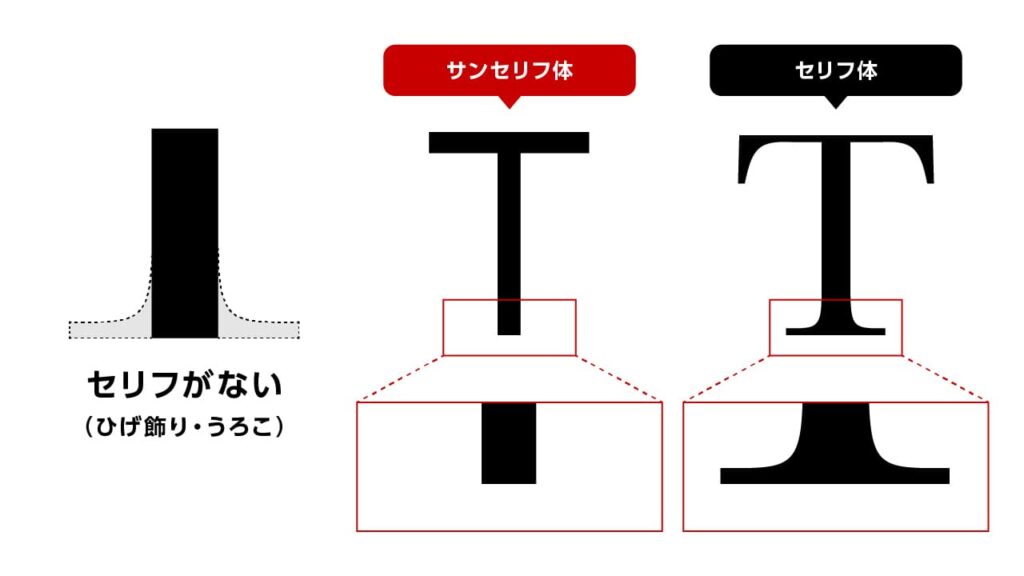
「sans」はフランス語で「〜が無い」という意味で、その名の通りセリフを省いたシンプルなデザインが特徴です。セリフ体(ローマン体)が文字の端に装飾を持ちクラシックで伝統的な印象を与えるのに対し、サンセリフ体は装飾のない分よりクリーンでモダンな印象を与え、デジタル画面でも読みやすいとされています。なお、欧文のサンセリフ体は日本語書体で言うところの「ゴシック体」に相当し、明朝体(セリフのある書体)と並ぶ基本的なカテゴリーです。サンセリフ体は簡潔な字形ゆえに視認性が高く悪条件下でも文字が判別しやすいという利点があり、新聞見出しや道路標識などパッと一瞥で内容を伝える場面で重宝されます。ただし従来、長文の可読性においてはセリフ体に劣るとも言われ、小説など連続した文章よりも見出しや短文向きの書体と位置付けられてきました。
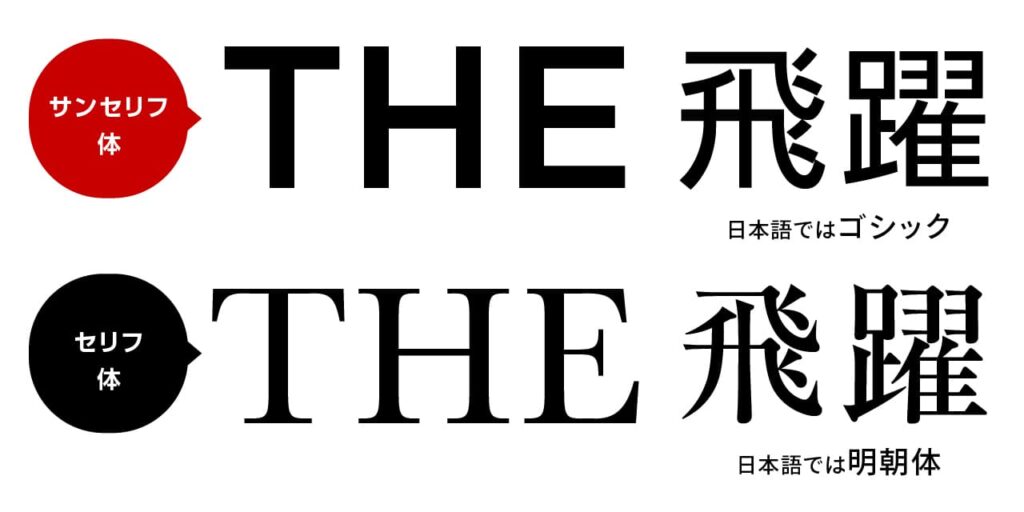
本記事では、サンセリフ体の歴史や分類、用途と印象の違い、さらに定番フォントの紹介と選び方のポイントについて解説します。セリフ体の基礎に続く内容として、デザイン初心者の方にも分かりやすくサンセリフ体の奥深い世界を見ていきましょう。
サンセリフ体の歴史的背景
サンセリフ体が登場したのは19世紀に入ってからで、書体の中では比較的新しい歴史を持つカテゴリーです。19世紀前半、工業化とともにポスターやチラシなど商業印刷物が発達する中で、遠くからでも目を引きはっきり読めるシンプルな見出し用書体が求められ、最初期のサンセリフ体の活字が生み出されました。当初この新奇な書体は「グロテスク(Grotesque)」あるいは「ゴシック(Gothic)」と呼ばれ、当時代表的なものにAkzidenz Grotesk(1898年、ドイツ)やFranklin Gothic(1902年、アメリカ)などがあります。これら初期のサンセリフ体は装飾を削ぎ落とした力強いデザインで、広告の見出しや看板などに活用されました。
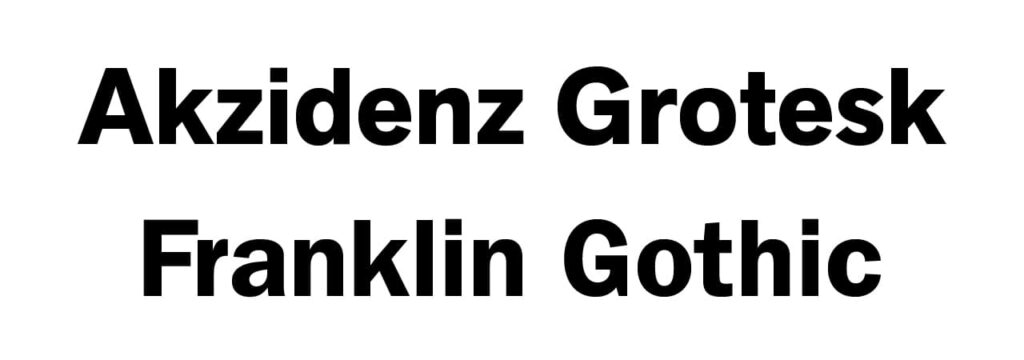
20世紀に入るとサンセリフ体はグラフィックデザインの潮流に合致したモダンで洗練されたルックスにより広く人気を博すようになります。例えば1920〜30年代には幾何学的デザインのFuturaや、古典書体のエッセンスを取り入れたGill Sansなどが登場し、さらに1950年代にはスイスを中心とする国際タイポグラフィ様式のもとでHelvetica(ヘルベチカ)やUnivers(ユニバース)といった洗練されたサンセリフ体が次々と開発されました。こうした書体は印刷物だけでなく企業のロゴやサイン計画にも採用され、サンセリフ体の地位を不動のものとしました。
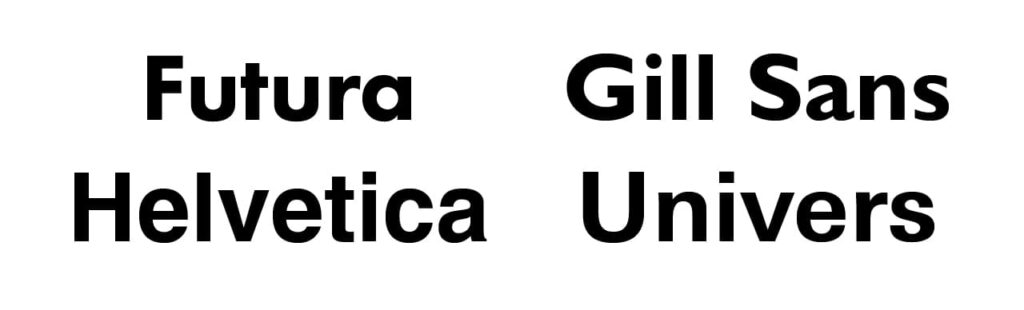
なお、サンセリフ体は以前「ゴシック体」と呼ばれることもありましたが、欧米では“Gothic”はブラックレター(黒字書体)を指すため紛らわしく、現在は国際的に「Sans-serif(サンセリフ)」という呼称に統一されています。
デジタル時代に入ると、サンセリフ体はその直線的でそぎ落としたデザインゆえに画面上で特に読みやすく、ウェブやユーザインタフェースの基本フォントとして欠かせない存在となりました。こうして約200年ほどの歴史の中で、サンセリフ体は印刷物からデジタル媒体まで幅広く活躍するモダン書体として定着しています。
サンセリフ体の主な分類と特徴
ひと口にサンセリフ体と言っても、そのデザイン上の特徴から大きく4つのグループに分類することができます。以下にグロテスク(Grotesque)、リアリスト(Realist)、 ヒューマニスト(Humanist)、ジオメトリック(Geometric)というサンセリフ体の主な分類とそれぞれの特色を説明します。
グロテスク・サンセリフ
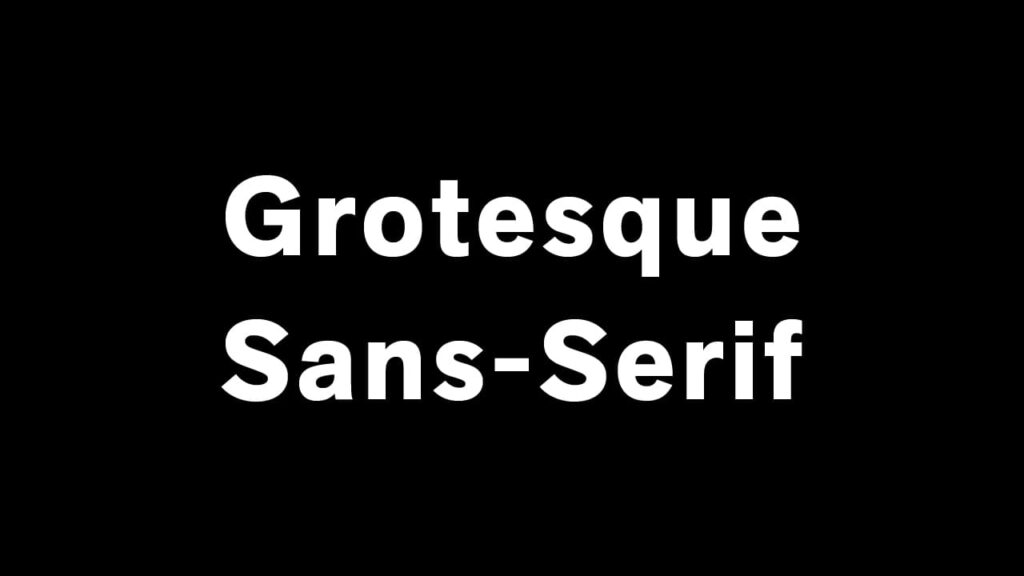
書体の特徴と背景
グロテスク・サンセリフは、サンセリフ体の最初期に登場した書体群で、19世紀から20世紀初頭にかけて生まれました。直線的で力強く、装飾のないシンプルなデザインが特徴で、当時はその異質な見た目から「グロテスク(奇妙)」と呼ばれました。
字幅の太さや端の処理にやや粗さがあり、全体的に武骨で頑丈な印象を与えます。視認性が高く、インパクトのあるデザインが求められる場面に適しています。
代表的な書体
- Akzidenz Grotesk(アクチデンツ・グロテスク)
ドイツで生まれ、後の多くのサンセリフ体に影響を与えた先駆的書体。 - Franklin Gothic(フランクリン・ゴシック)
アメリカで開発され、広告や新聞の見出しなどに多用された、力強さのあるフォント。
使用シーン
太く力強いグロテスク体は、ヴィンテージ感や男性的な印象を与えたいデザイン、広告・ポスター・見出しなどに最適です。
リアリスト・サンセリフ(ネオ・グロテスク)
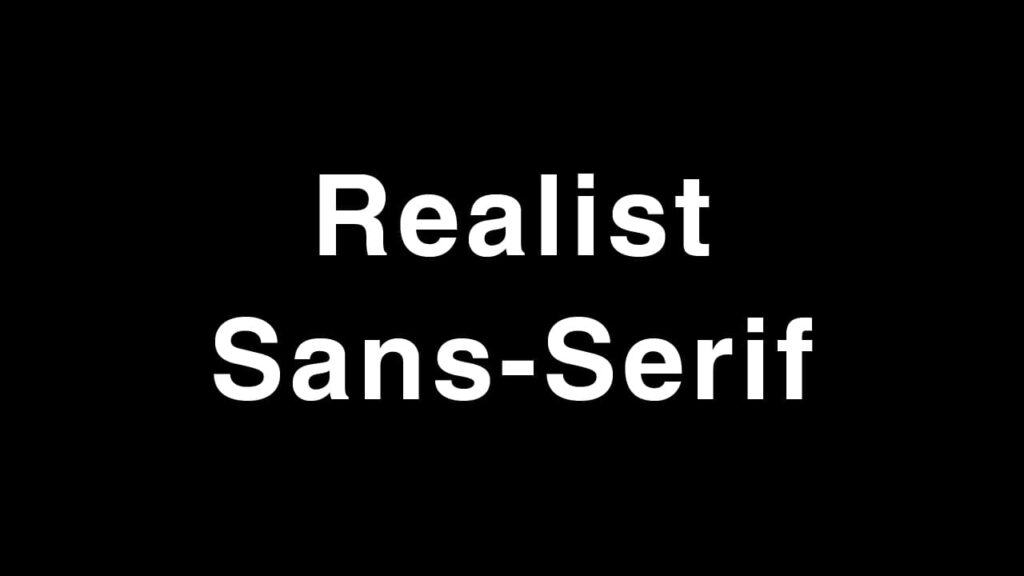
書体の特徴と背景
リアリスト・サンセリフは、グロテスク体を洗練し、より現代的に整えたスタイルです。1950年代前後に登場し、「ネオ・グロテスク」とも呼ばれます。
癖の少ないスマートな字形、均一な線幅、高い視認性と汎用性が特徴で、どんな媒体にも適応する中立的かつ万能なフォントです。
代表的な書体
- Helvetica(ヘルベチカ)
スイス生まれ。世界的に使用されており、ロゴ・標識・UIなど幅広い用途に対応。 - Univers(ユニバース)
多様なウエイト・スタイルを持つ、体系的に設計されたフォントファミリー。 - Arial(エリアル)
Microsoftに標準搭載された汎用フォント。画面表示に強く、文書やウェブにも適しています。
使用シーン
資料・UI・ウェブ・コーポレートデザインなど、癖のない安定感を求める場面に広く活用されます。
ヒューマニスト・サンセリフ
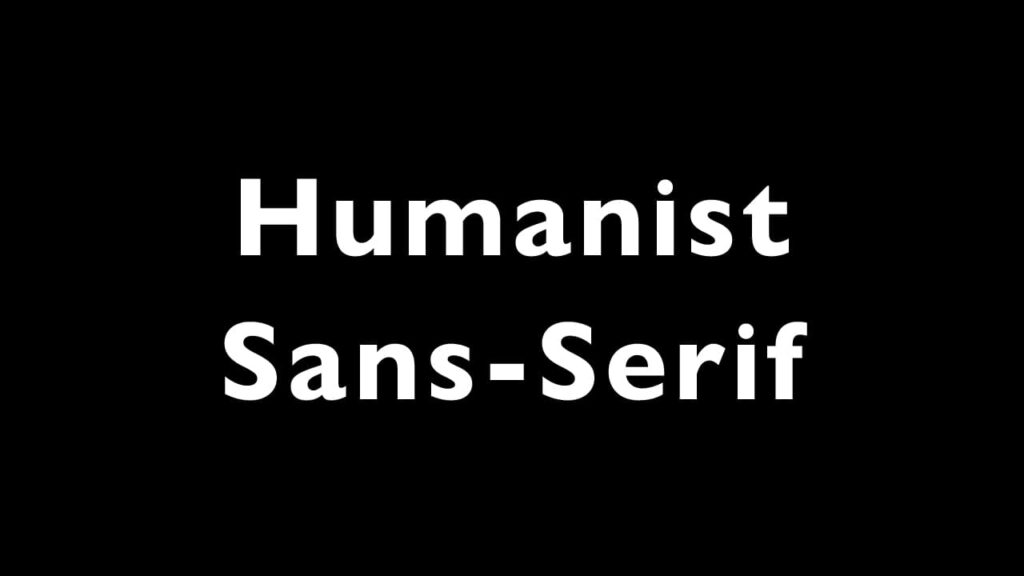
書体の特徴と背景
ヒューマニスト・サンセリフは、人の筆記のニュアンスを反映した、人間味のあるデザインが特徴です。古典的なセリフ体の骨格をベースにし、滑らかな曲線と抑揚のあるストロークが温かみを生み出します。
「読みやすさ」だけでなく、「優しさ」や「親しみやすさ」といった感情的な印象を与えるサンセリフ体です。
代表的な書体
- Gill Sans(ギル・サン)
英国で開発され、公共デザインやテレビ局などに多く採用。柔らかく上品な印象。 - Frutiger(フルティガー)
空港サイン向けに開発。可読性が非常に高く、案内表示などに多用。 - Verdana(ヴァーダナ)
画面表示用に最適化されたデザイン。小サイズでも読みやすく、WebやUIに強い。
使用シーン
教育・医療・公共サインなど、人にやさしく寄り添う印象を与えたいときに適しています。
ジオメトリック・サンセリフ
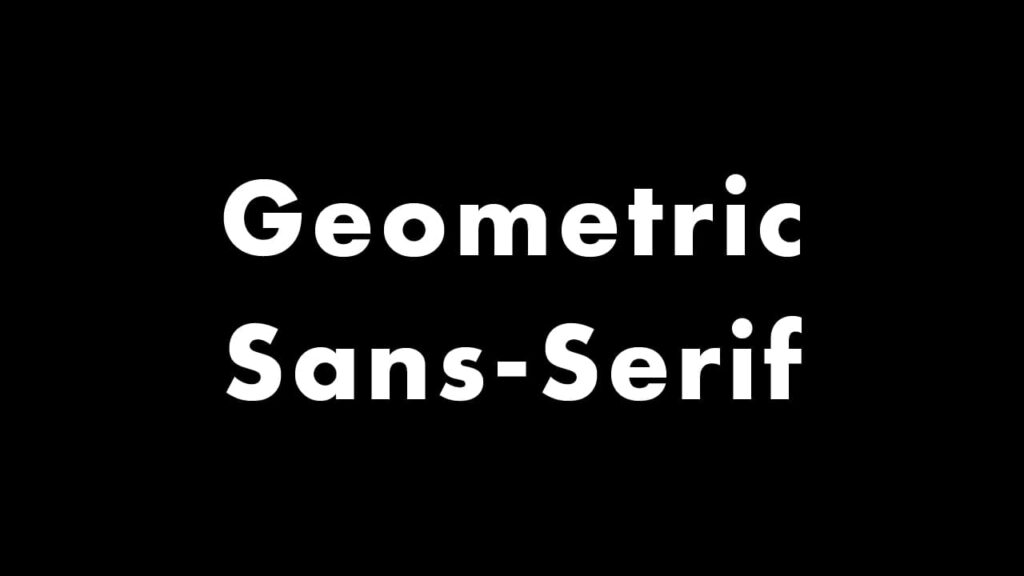
書体の特徴と背景
ジオメトリック・サンセリフは、円・直線・三角形などの幾何学図形を基に設計された書体です。1920年代のドイツ・バウハウスの思想を背景に誕生し、構造的でモダンなデザインが特徴です。
均整の取れた美しい字形は、先進性・創造性・理知的な印象を与えます。
代表的な書体
- Futura(フーツラ)
幾何学デザインの先駆け。シンプルかつ未来的な印象で、ロゴやポスターに人気。 - Avenir(アベニール)
Futuraに比べて読みやすさを重視。バランス感があり、本文にも対応。 - Gotham(ゴッサム)/ITC Avant Garde
ロゴやブランド用として人気。洗練されたスタイルで現代的な印象を演出。
使用シーン
ファッション・IT・広告など、ブランドの先進性やスタイリッシュさを訴求したいデザインに最適です。
サンセリフ体の用途と印象
サンセリフ体は、視認性・中立性・現代性を備えた非常に実用性の高い書体であり、紙媒体からデジタル、公共から広告、教育からビジネスまで幅広い用途に対応できる汎用性があります。
伝えたい印象や用途に応じて適切なサンセリフ体を選ぶことで、デザインの説得力や完成度を大きく高めることができます。
サンセリフ体が持つ基本的な印象とは
サンセリフ体は、装飾のないクリーンな字形と高い視認性から、さまざまな場面で重宝される書体です。セリフの有無による印象の違いは、デザインメッセージの伝わり方に直結します。
たとえば、セリフ体は「伝統的」「格式が高い」「権威的」といった印象を持たせやすく、証書や招待状などフォーマルなデザインに向いています。一方、サンセリフ体は「新しさ」「モダンさ」「カジュアルさ」を表現しやすく、ハイテク企業のウェブサイトや先進的な印象を打ち出したい場面に適しています。
実用性の高さと視認性の強さ
サンセリフ体のもうひとつの大きな強みは、小さなサイズでも潰れにくく、遠目でも認識しやすいという点です。これは、ストロークに装飾的な突起がないためです。
そのため、道路標識、取扱説明書、新聞や辞書の見出し、広告ポスターなど、一目で情報を伝えたい媒体で広く使用されています。また、プレゼン資料やインフォグラフィックスでも、サンセリフ体は読みやすく、プロフェッショナルな印象を与えるため、ビジネスシーンにも適しています。
デジタルメディアとの相性の良さ
サンセリフ体は、デジタル環境でも非常に高い可読性を発揮します。
ディスプレイの解像度が低い場合でも、セリフのような細かな装飾がないため、文字の視認性が損なわれにくいという利点があります。そのため、ウェブサイトやモバイルアプリ、ソフトウェアUIでは、サンセリフ体が基本書体として選ばれることが多く、実際に、WindowsのSegoe UIやMacのSan Franciscoなど、主要OSの標準フォントもすべてサンセリフ体で構成されています。
印象を変えるフォントの個性
「サンセリフ体=無個性」ではありません。むしろ、装飾が少ない分、フォントの骨格そのものの表情が際立ちます。そのため、選ぶフォントによって与える印象は大きく変わります。
- ヒューマニスト系:柔らかく親しみやすい印象。教育・公共の場に最適。
- リアリスト系:ニュートラルで信頼感のある印象。金融・法律・ビジネス用途に適す。
- ジオメトリック系:スタイリッシュで先進的な印象。ハイテク・ファッションブランドに人気。
実際、GoogleやFacebookをはじめ、多くのグローバル企業がサンセリフ体のロゴを採用しているのは、ニュートラルでフラットな印象が、多様な文化背景を持つユーザーにも受け入れられやすいためです。
定番のサンセリフ体フォント紹介
ここではデザイナー志望なら知っておきたい定番のサンセリフ体フォントを、前述の分類ごとにいくつか紹介します。それぞれのフォントの特徴や使用シーンの例も添えますので、ぜひ実際に使ってみる際の参考にしてください。また、紹介するフォントはAdobe Fontsで使用できますので、リンク情報を貼っておきますね。
グロテスク・サンセリフの定番フォント
Akzidenz Grotesk
Akzidenz Grotesk(アクチデンツ・グロテスク)は1898年にドイツで生まれた最初期のサンセリフ体の一つ。無駄のないシンプルなデザインで後のHelveticaなど多くの書体のお手本となりました。太さや大きさを変えた幅広いファミリー展開があり、中立的で癖のないスタイルは企業デザインから標識まで幅広い用途で利用されています。
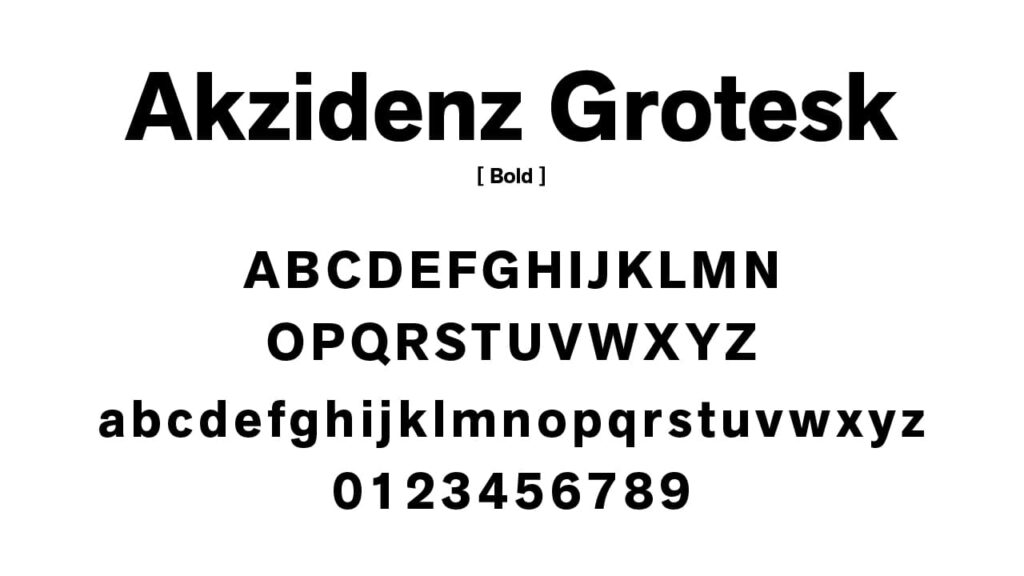
Franklin Gothic
Franklin Gothic(フランクリン・ゴシック)は、1902年にアメリカで発表されたグロテスク体書体。古典的でやや粗削りな力強さが持ち味で、男性的で堂々とした雰囲気を醸し出します。見出しやポスターでインパクトを与えたい時に適しており、新聞の見出しや大学スポーツチームのロゴなどにも用いられました。太く大ぶりな字形は遠目にも目立つため、広告物で強い存在感を放ちます。
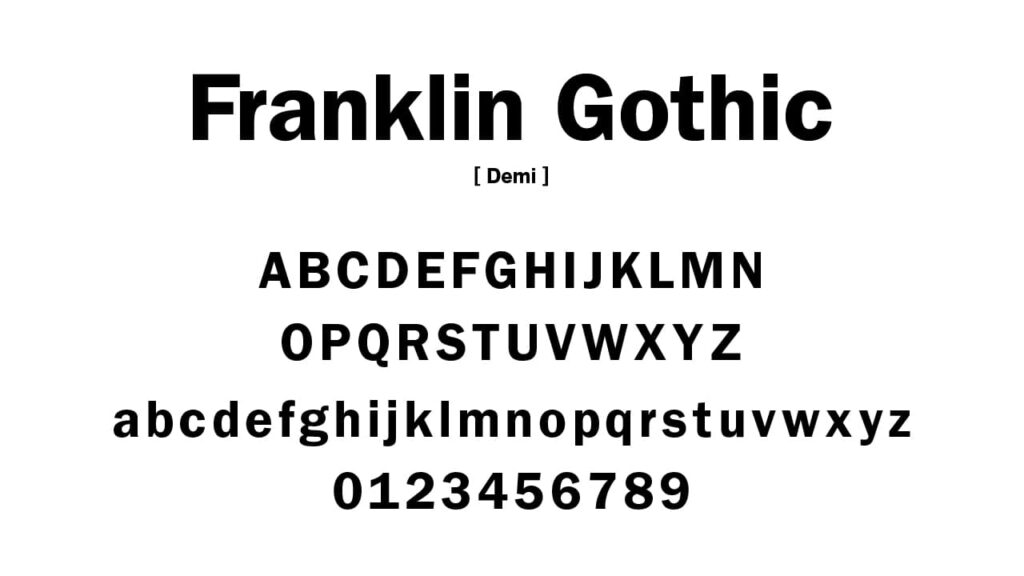
DIN
DIN(ディン)は20世紀前半にドイツ工業規格(DIN)として制定されたサンセリフ体で、道路標識や案内表示に採用されたことでも有名です。直線的で均一なストロークによる工業的デザインは可読性が高く、無駄のないクールな印象を与えます。現代ではその洗練されたスタイルから、モダンでミニマルなブランドのロゴや、サイエンス・テクノロジー系のデザインなどにも広く活用されています。
リアリスト・サンセリフの定番フォント
Helvetica
Helvetica(ヘルベチカ)は1957年にスイスで生まれ、世界で最も愛用されているサンセリフ体の一つです。名前はラテン語で「スイス」を意味する「Helvetia」に由来します。シンプルで洗練された美しさを持ち、ニュートラルかつ汎用的なデザインであることから多数の企業ロゴや公共サインに採用されています。例えばニューヨーク市地下鉄の標識やユニクロのロゴなど、 Helvetica が使われた有名な例は数えきれません。どんな媒体でも安定して読みやすく、「究極のスタンダードフォント」として知られます。
Univers
Univers(ユニバース)は、Helveticaと同じ1957年に生まれたフランス発のサンセリフ体。デザイナーのエイドリアン・フルティガーによって体系的なファミリーとして設計されたことが特徴で、太さや幅の異なる21種類ものバリエーションを持つ包括的なフォントファミリーです。字形のデザインは非常に均整が取れており、Helveticaよりやや人間味のある柔らかさも備えています。印刷物からディスプレイまで万能に使える書体として、スイス航空やモトローラ社のコーポレートフォントに採用されるなど信頼性の高いブランド表現に貢献してきました。
Arial
Arial(エリアル)は1982年に開発され、現在ではWindowsやOffice製品に標準搭載されているため誰もが目にしたことのあるサンセリフ体です。Helveticaに似たデザインを持ちつつ画面表示に最適化されており、デジタル文書やWeb上の標準フォントとして広く利用されています。特にウェブの本文やプレゼン資料のテキストなど、読み手の環境を問わず確実に表示させたい場面で重宝されます。Arial自体はデザイン的に強い個性を主張しない分、内容を邪魔せず情報伝達に徹する実用的なフォントと言えます。
ヒューマニスト・サンセリフの定番フォント
Gill Sans
Gill Sans(ギル・サン)は1928年にイギリスのエリック・ギルによってデザインされた書体で、ヒューマニスト・サンセリフを代表するフォントの一つです。古典的なトラジャン石碑の文字にヒントを得たプロポーションを持ち、優雅さとモダンさを兼ね備えた独特の風格があります。イギリスでは国営鉄道のサインやBBCのロゴなどに採用され、公共的で信頼感のあるイメージを与えてきました。柔らかな曲線とオープンな字面により、堅苦しすぎず親しみやすい印象を与えるため、教育・文化施設や雑誌のデザインなどにも適しています。
Frutiger
Frutiger(フルティガー)は、1975年にスイス人デザイナーのエイドリアン・フルティガーによって制作されたフォントで、フランスのシャルル・ド・ゴール空港のサイン用書体として開発されました。遠くからでも判別しやすいよう設計されており、広いカウンター(字の内部の空間)と開放的な字形が特徴です。非常に高い視認性から世界中の空港や道路標識で採用されているほか、現代では企業のコーポレートフォントとしても人気があります。Frutigerはヒューマニスト書体の中でもクセが少なく上品なため、大量のテキストを扱う報告書やウェブ文章にも適しています。
Verdana
Verdana(ヴァーダナ)は1996年にマイクロソフト社向けに開発されたサンセリフ体で、画面表示での読みやすさを徹底追求している点が最大の特徴です。デザイナーは有名なタイプデザイナーのマシュー・カーターで、小サイズでも判読しやすいよう文字間の間隔や文字の幅がゆったりと設計されています。特に小文字の「i」や「l」など紛らわしい字形にも工夫が凝らされ、初期のWebブラウザやWindowsシステムフォントとしても採用されました。Verdanaは装飾を排したモダンさと人間的な温かみを併せ持ち、デジタルコンテンツや電子書籍、プレゼン資料などで現在も利用頻度の高い信頼できるフォントです。
ジオメトリック・サンセリフの定番フォント
Futura
Futura(フツラ/フーツラ)は、1927年にドイツのパウル・レナーがデザインしたジオメトリック・サンセリフの代表格です。円や三角形など基本図形を組み合わせた幾何学的な字形は発売当時「未来的」と評され、その名の通り未来志向でモダンな印象を与えます。ルイス・バラガンやバウハウスなどモダニズム文化の影響を受け、第二次世界大戦後の広告やポスター、企業ロゴ(例:Volkswagenの旧ロゴ)にも広く採用されました。文字の高さ(Xハイト)が高く均整の取れたデザインのため、見出しやキャッチコピーに用いるとシャープで洗練された雰囲気を演出できます。
Avenir
Avenir(アベニール)は、1988年にFrutigerなどを手掛けたエイドリアン・フルティガーによってデザインされた書体で、フランス語で「未来」を意味します。その名が示す通りFuturaの系譜を継ぐジオメトリック・サンセリフですが、単純な幾何学形に留まらず可読性と均衡の良さを追求している点が特徴です。例えば「O(オー)」の字は完全な真円ではなく僅かに縦長に設計されており、文章中での読みやすさが向上しています。Avenirは上品さとモダンさを兼ね備えており、欧米の銀行や美術館のVI(ビジュアル・アイデンティティ)にも採用されるなど、高級感や信頼感を演出したい場面で活躍しています。
Gotham
Gotham(ゴッサム)は、2000年に発表された比較的新しいジオメトリック・サンセリフ体です。ニューヨークの街角看板のレタリングから着想を得ており、クラシックな幾何学要素と現代的な太さ・バランスが融合したデザインになっています。どっしりと安定感がありつつ親しみやすい字形が評価され、2008年のアメリカ合衆国大統領選挙でオバマ陣営がキャンペーンロゴに採用したことで一躍有名になりました。その後も多くの企業ロゴや雑誌タイトルに使われており、現代的でありながら信頼感のあるブランドイメージを打ち出すフォントとして人気です。太さのバリエーションも豊富で、極細から極太まで多彩なウェイトを組み合わせることで柔軟なデザイン表現が可能です。
サンセリフ体の選び方と使用上の注意点
最後に、サンセリフ体フォントを選ぶ際のポイントや使用上の注意点を整理します。デザイン初心者の方は以下の点に留意しながらフォント選択をすると良いでしょう。
まとめ
サンセリフ体は、その装飾を削ぎ落とした洗練されたデザインによって、現代のデザインにおいて欠かせない存在となっています。モダンで視認性に優れたサンセリフ体は、印刷物の見出しからデジタル画面の本文テキスト、企業ロゴや公共サインまで幅広い用途で活躍し、私たちに情報をわかりやすく伝えてくれます。この記事ではサンセリフ体の歴史的な背景から主要な分類、それぞれの特徴や代表フォント、さらに選び方のポイントまでを解説しました。セリフ体とは異なる魅力を持つサンセリフ体の世界を理解することで、デザインの幅は一段と広がるはずです。
初学者の方は、まず本記事で紹介した定番フォントから実際に使ってみることをおすすめします。例えば、ロゴやタイトルにはジオメトリック系のFuturaでモダンな印象を演出し、本文にはヒューマニスト系のGill Sansで親しみやすさを出す、といった組み合わせを試してみると良いでしょう。サンセリフ体は一見シンプルですが、その中にも多彩な表情と奥深さがあります。ぜひ様々なサンセリフフォントを使い比べて、それぞれの書体が持つ個性や効果を体感してみてください。タイポグラフィの基本を押さえつつ、自分のデザインに最適な一書体を選び取れるようになれば、デザイナーへの第一歩として大きな武器になることでしょう。新米デザイナーの皆さんがサンセリフ体を自在に使いこなし、魅力的なデザイン作品を生み出せることを期待しています。